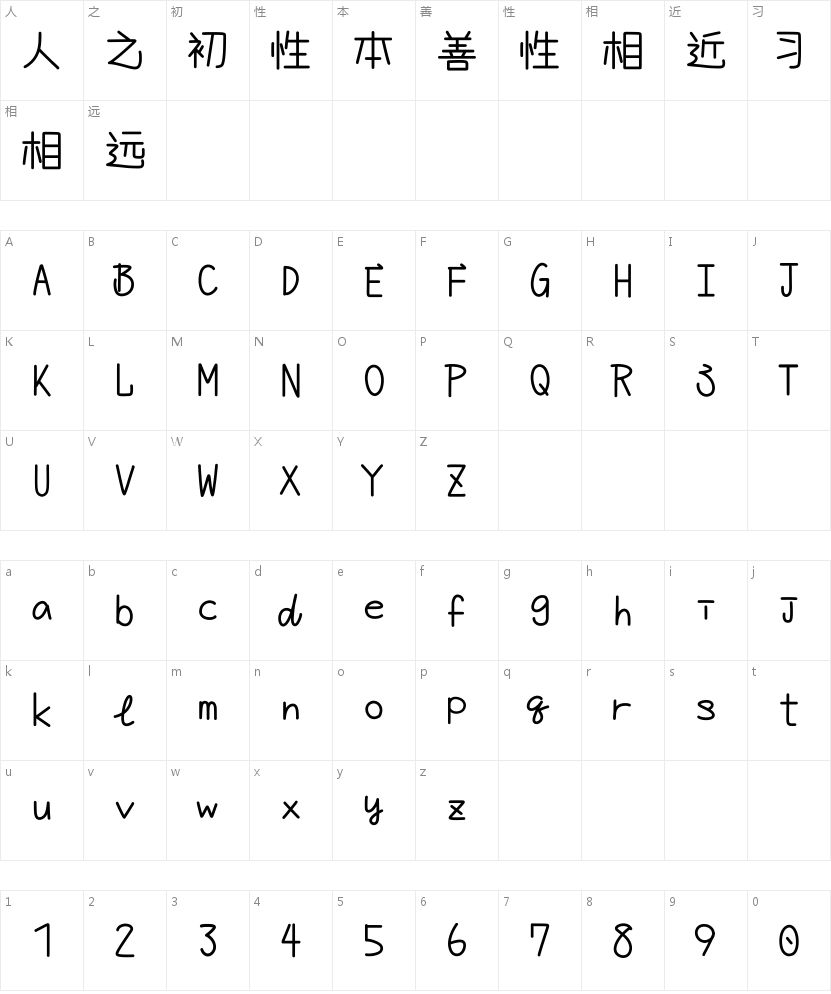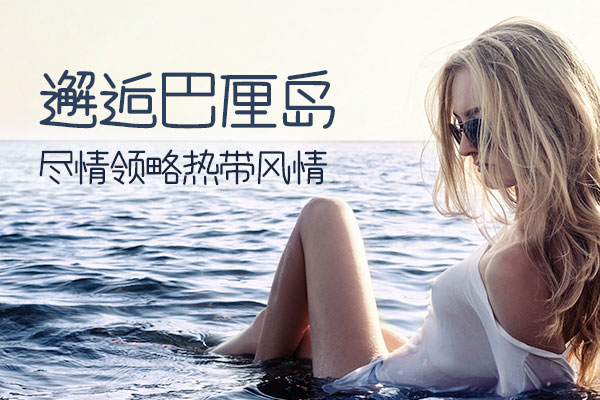
宅在家自动笔的简体和繁体支持都表现得相当出色,已经完全覆盖了简体国标GB2312的6763个汉字,这意味着无论在处理简体还是繁体中文时,它都能表现出众,基本不存在缺字现象。无论是设计师还是普通用户,都可以放心使用这款字体来呈现各种文字内容。
这款字体的设计灵感源于人们手写汉字的独特风格,让人感受到一股亲切与自然。它的出现无疑为许多字体设计师和广大文字工作者提供了极大的便利。让我们一起期待“天天宅在家”未来更多精彩的字体作品吧!